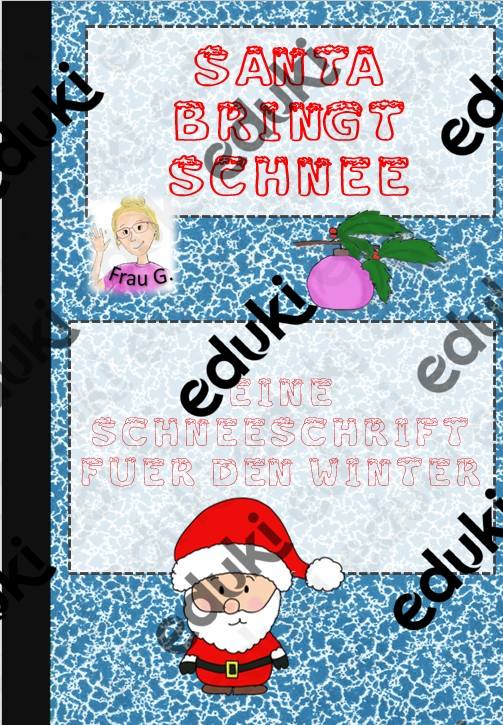
selbst erstellte Schriftarten - Schriftart Santa Schnee - FrauGPunkt - Deckblatt
Eine gezeichnete Schrift mit Schnee.
Achtung - es handelt sich ausschließlich um Großbuchstaben!
Schriftart Santa Schnee